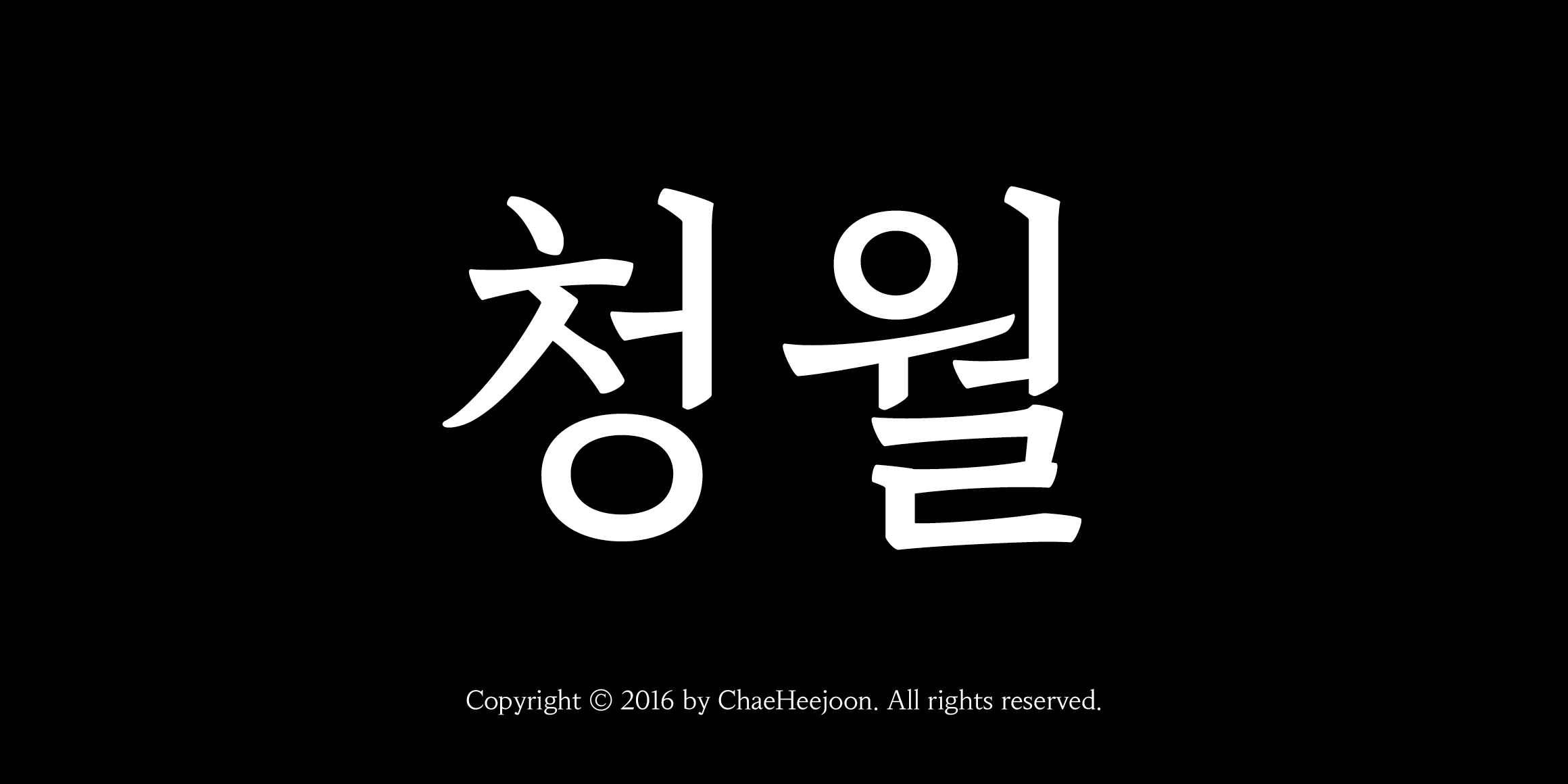
청월
청월은 1797년에 간행된 『오륜행실도』의 한글 활자를 참조해 구조를 현대화한 세로쓰기용 본문 글꼴이다. 옛 활자로부터 반영한 요소들로 인해 예스러운 분위기가 담겨져 있고, 정방형의 몸집과 큼직한 받침 등에서 특유의 조형미가 나타난다. 2016년에 최초 버전이 출시되었으며, 2019년에 업데이트한 1.5버전에서 기호활자들과 한글 20자가 추가되어 스펙이 변동되었다. 또한 한글 속공간에 대한 전반적인 수정과 영문 및 문장부호의 형태들을 새롭게 교체하면서 디자인적인 변화도 이루어졌다.
• 세리프
• 청월 / Cheongweol
• 한글 2,370자 / 로만 알파벳 52자 / 숫자 및 약물 354자